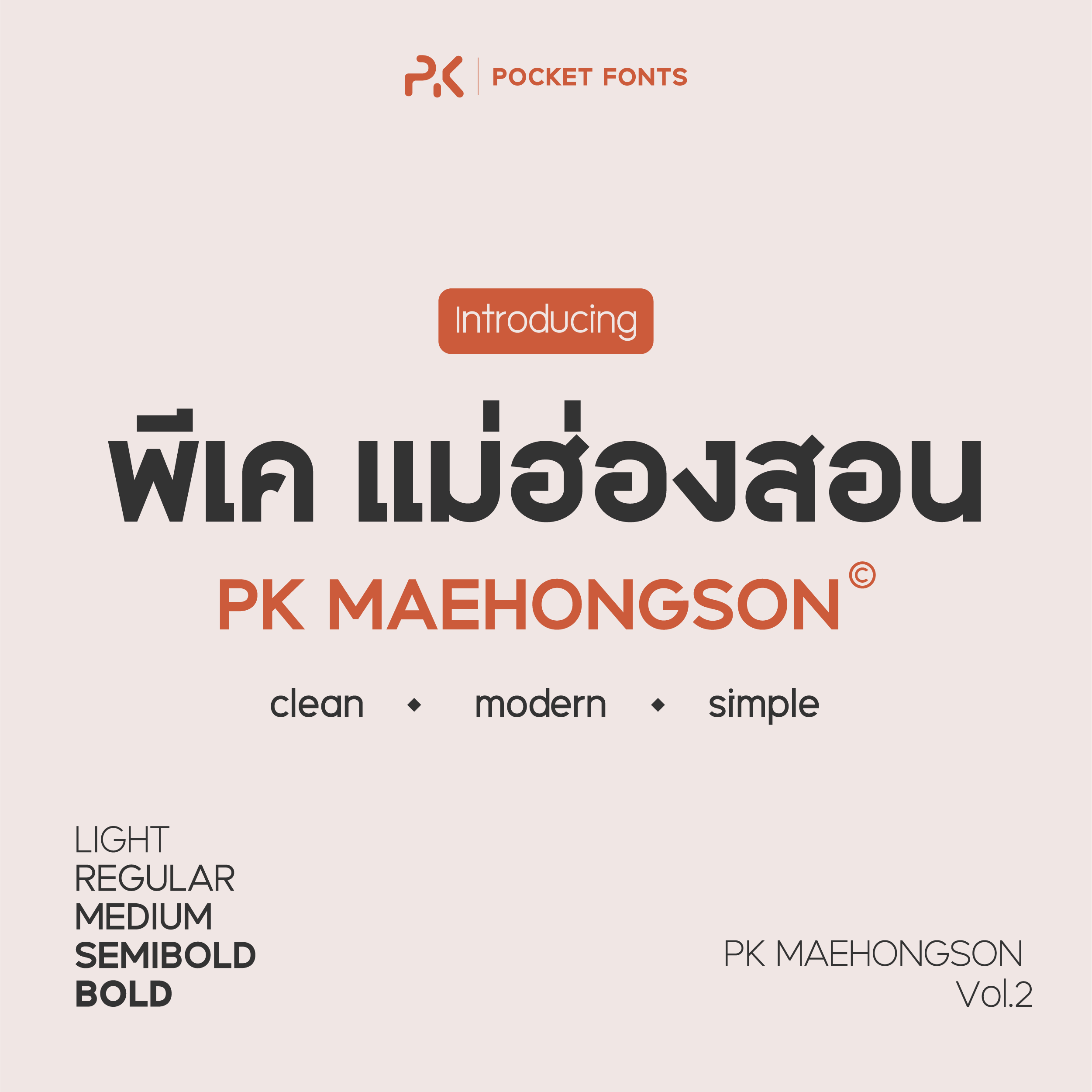
พีเค แม่ฮ่องสอน v.2 | PK Maehongson v.2
ชื่อฟอนต์ พีเค แม่ฮ่องสอน v.2 | PK Maehongson v.2
เป็นฟอนต์สไตล์ มินิมอล เรียบง่าย เป็นระเบียบและอ่านง่าย เข้ากับงานได้หลากหลายประเภทไม่ว่าจะเป็นบนเว็บไซต์ งานกราฟิกโฆษณา หรืองานป้ายก็ดี เพราะมีหลากหลายน้ำหนัก
จากกระแสตอบรับค่อนข้างดีและมีหลายท่านต้องการให้ทำฟอนต์ พีเค แม่ฮ่องสอน ให้มีน้ำหนักเพิ่ม วันนี้ก็พร้อมแล้ว สำหรับ พีเค แม่ฮ่องสอน v.2 ที่เพิ่มน้ำหนัก จาก 3 เป็น 5 น้ำหนักตามคำเรียกร้อง และยังปรับให้เป็น variable font ปรับน้ำหนักได้อย่างละเอียดในซอฟท์แวร์ที่รองรับ